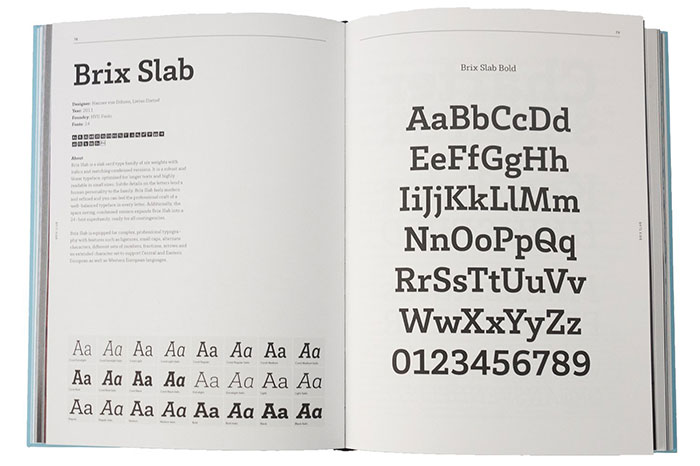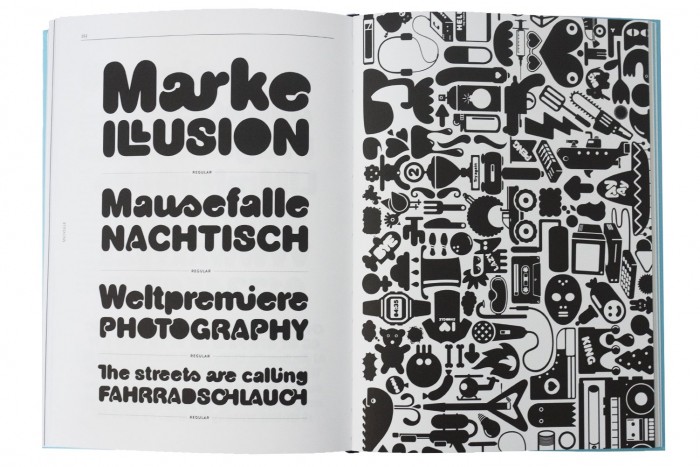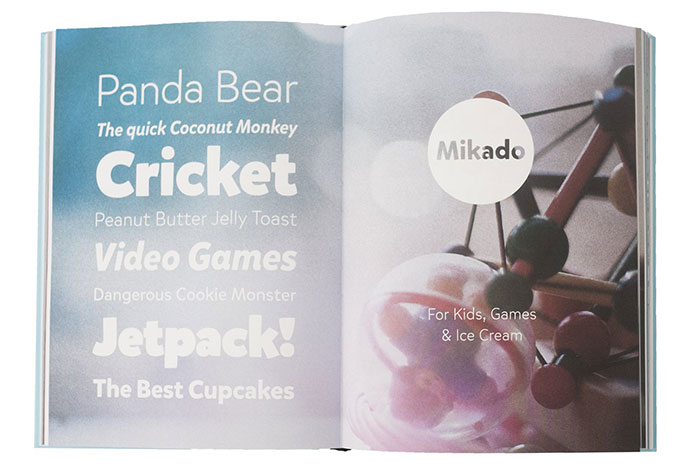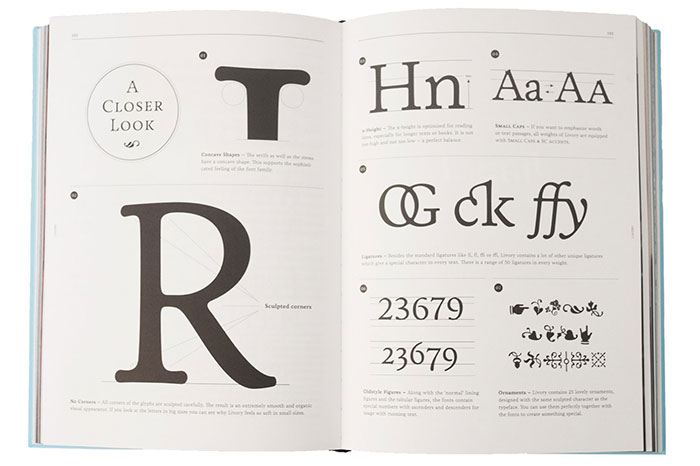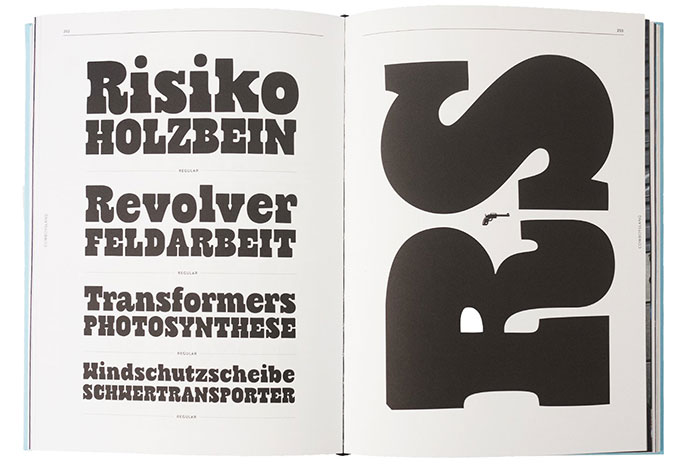
Vor 100 Jahren im Bleisatz waren Schriftproduktion und Vertrieb noch so teuer, dass sich die Bestseller unter den Schriften meist nur bei den großen, finanzstarken Schriftgießereien fanden. Mit der Digitalisierung der Schrift und offenen, weltweit zugänglichen Vertriebsplattformen wie MyFonts können heute aber auch schriftgestalterische »Einzelkämpfer« in kurzer Zeit Bekanntheit erlangen. Vor einigen Jahren war etwa der Niederländer Jos Buivenga einer der ersten der neuen »MyFonts-Stars«. Ein Schriftgestalter, der aktuell mit fast jeder neuen Schrift in die Bestseller-Listen einsteigt, ist der Berliner Hannes von Döhren mit seinem Label HvD Fonts. In einem beim »Hermann Schmidt Verlag« erschienenen Buch stellt er nun sein Schriftschaffen der letzten sechs Jahre vor.
Den größten Teil des 272 Seiten starken und komplett englischen Festeinband-Buches machen die Vorstellungen bzw. Präsentationen von 31 Schriftentwürfen aus. Die Aufmachung entspricht den üblichen Schriftmustern, wie man sie heute meist digital auf Webseiten und in PDFs vorfindet: ein kurzer (werblicher) Beschreibungstext, Alphabet-Übersichten sowie fiktive Textdarstellungen mit Einzelwörtern und Blindtextabsätzen.
Angereichert wird das Buch von einem Fachtext von Jan Middendorp, der über Hannes von Döhren und die neuen Möglichkeiten des Schriftvertriebes schreibt. Außerdem gibt es zwei Interviews: eines mit Hannes von Döhren und eines mit Freund und Mitarbeiter Livius Dietzel. Am Ende des Buches gibt es eine Bildersammlung mit HVD-Fonts in realen Anwendungen.
Fazit: Das Werk ist vor allem ein Schriftmusterbuch, das sämtliche HvD-Fonts in gedruckter Form zeigt – früher hätte man von einer so genannten Hauptprobe gesprochen. Jedoch waren solche Schriftmuster in der Regel kostenlos, denn sie waren vor allem Werbematerial, das zum Schriftenkauf animieren sollte. Mit einem Kaufpreis von 39,80 Euro ist das hier vorliegende Schriftmusterbuch in diesem Sinne vergleichsweise teuer und bietet abgesehen von der Druckform der Schriftmuster inhaltlich leider kaum einen Mehrwert – man denke etwa an mögliche tiefer gehende Hintergrundinformationen zu den Schriftentwürfen, Skizzen und Anekdoten aus dem Gestaltungsprozess oder schriftgestalterische Einordnungen und Analysen, aus denen der Leser des Buches etwas lernen könnte. Schade! Für knapp 40 Euro sind mir rein werbliche Schriftmuster zu wenig. So kann ich leider keine allgemeine Kaufempfehlung aussprechen und das Buch nur eingefleischten Schriftmustersammlern und Von-Döhren-Fans empfehlen.
Untertitel: The HVD Fonts TYPE BOOK.